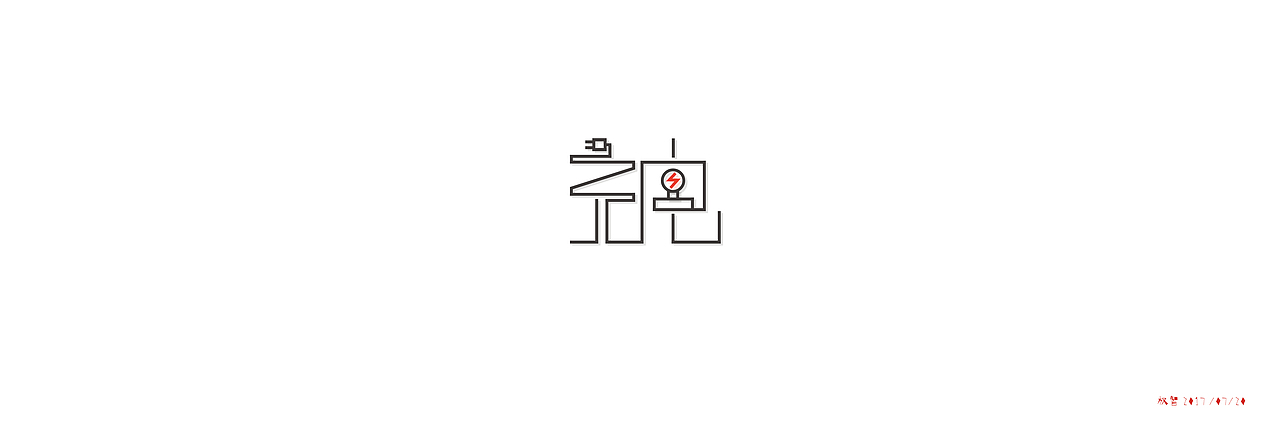
字体练习-充电
今天天气特别热,寝室真的很热(学校穷、没空调),我的充电器忘在了公司,手机就没电了,连续实习两周只休息一天的我也是需要充电了,于是就想起今天就做“充电”二字,加之今天开始看刘兵克老师的书(自由字在)看到其中一个字型分析,有用到充电线的元素。于是就有了今天的小练习。加油。望大神指导!感激不尽!